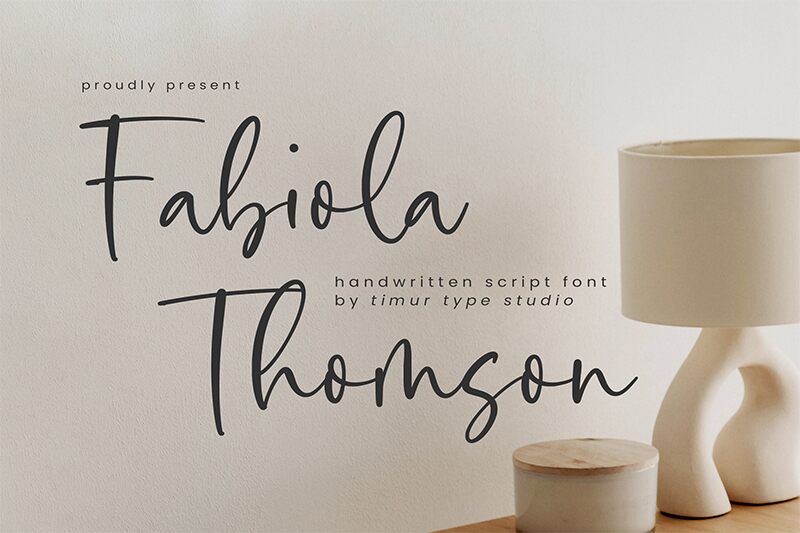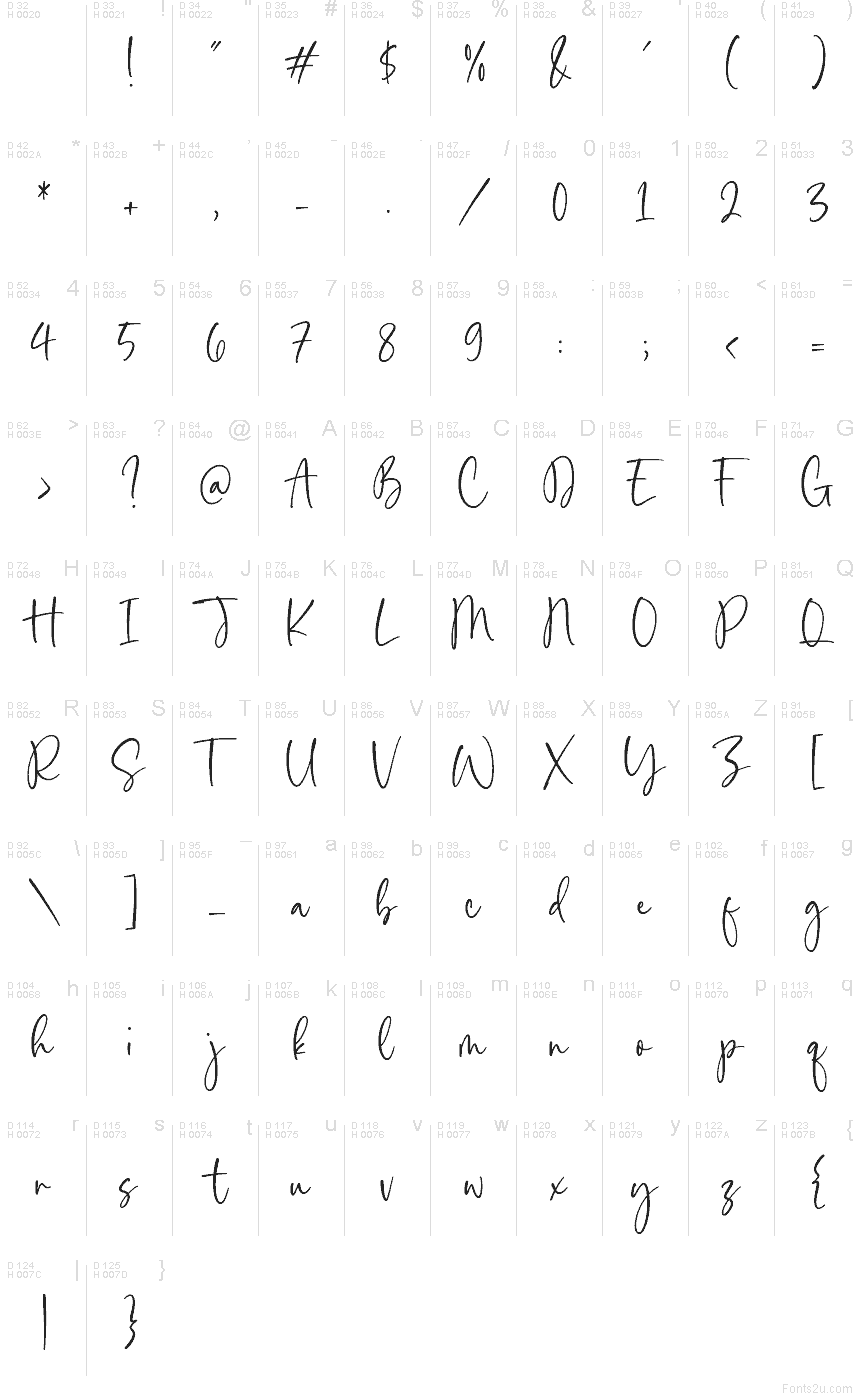
Fabiola Thomson
Fabiola Thomson від Timur Type Studio — це безкоштовний рукописний шрифт з вільним стилем підпису та високими, плинними літерами. Він зберігає невимушений ритм завдяки довгим штрихам, заокругленим з'єднанням і природному почерку, який виглядає по-справжньому живим та індивідуальним.
Fabiola Thomson чудово підходить для весільних запрошень, логотипів, графіки з цитатами, листівок, постів у соцмережах та брендингу, оскільки його неформальний характер додає дизайну особистого акценту. Цей безкоштовний шрифт вносить рукописний шарм у короткі заголовки, імена та декоративні підписи, де невимушений, авторський вигляд важливіший за сувору структуру.
Fabiola Thomson — це рукописний шрифт від Timurtype Studio.
Шрифт Fabiola Thomson також підтримує багатомовність.